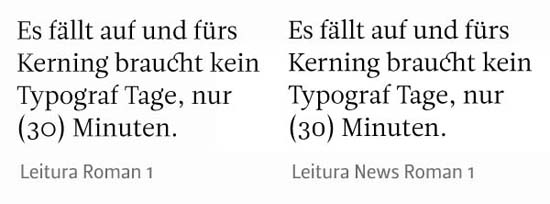
gerade habe ich das Leitura-Sonderangebot bei MyFonts gesehen. Es juckt mich ja in den Fingern: Ich bin als Naturwissenschaftler immer auf der Suche nach Schriften, die nüchtern und lesetexttauglich sind. Was ich bisher von der Leitura gesehen habe läßt mich denken, daß man sie gut auch für wissenschaftliche Aufgaben verwenden kann und die passende Serifenlose für Kapitelüber- und Bildunterschriften macht das Ganze noch attraktiver.
Meine eigentlich Frage: Hat jemand von Euch einmal mit diesem Schriftsystem gearbeitet? Wenn ich sie mir kaufe, dann möchte ich gerne sicher gehen, daß auch Details stimmen. In diesem Sinne: Weiß jemand von Euch, ob die Schriften der Leitura mit ordentlichen Kerning-Informationen daher kommen? Sicher, etwas nacharbeiten muß immer, aber manche Schriften sind weniger anfällig als andere (bei der Palatino gibt es z.B. weniger Kollisionen als bei der Garamond etc.). Und weiterhin: Ist die Leitura anständig gehintet? Ich habe mich hier einige Zeit an der Lido von Herrn Storm probiert, welche ich im Druck sehr schön finde, aber das mangelnde hinting ging mir dann nach einiger Zeit doch furchtbar auf den Geist (ja, ich weiß, einem geschenkten Gaul ...).
Weiß jemand von Euch näheres?
prinzipiell stimme ich Dir ja zu. Nun kenne ich allerdings die Verkaufspolitik von DSType nicht und habe bisher auch nicht mit Schriften von denen zu tun gehabt. Es kann ja sein, daß sie durch eine mehr oder weniger geschickt angelegte Aktion Werbung machen wollen. In diesem Fall könnte es sich durchaus um qualitativ recht hochwertige Schriften handeln. Ich bin mir durchaus bewußt, daß Qualität eben seinen Preis hat. Aber man kann eben auch einfach mal Glück haben, insbesondere bei Werbeaktionen. Habe vor Jahren mal einen originalen »Leatherman« als Werbegeschenk bekommen (natürlich mit Werbung auf dem Griff, aber wen stört sowas?). Sowas ist selten, kommt aber durchaus mal vor.
Ich hab die "Esta" von Dino dos Santos im Einsatz und kann nicht meckern (vielleicht bin ich auch nicht anspruchsvoll genug?). DSType ist halt auch ein Ein-Personen-Stück ...
ich habe auch einige von dinos fonts, kann auch nicht meckern – bis auf die namensgebung scheint alles ok zu sein. die schriften erscheinen bei mir nicht als eine familie mit schnitten im untermenü sondern alle einzeln. etwas kaotisch aber ich kann damit leben.
nach einigem Überlegen habe ich mir die Leitura tatsächlich gekauft und bin bisher insgesamt recht zufrieden. Die Namensgebung ist in der Tat etwas merkwürdig und die kursiven Schnitte erscheinen nicht als Unterpunkte, aber auch ich kann damit leben. Insgesamt denke ich, daß es sich für den Preis tatsächlich eher um ein Schnäppchen gehandelt hat.
Eines hat mich allerdings überrascht: Die mediävale Ziffer 0 der Leitura erscheint mir mißraten. Sie ist zu dünn und zu weit, reißt Löcher in den Satz:
Nun bin ich natürlich Banause. Ist das gewollt so? Gibt es einen Grund, warum die »0« so gestalltet ist, wie sie eben ist? Und den krassen Gegensatz zur 0 der Leitura News? Oder würdet Ihr zustimmen, daß das einfach nur merkwürdig aussieht? :oops:
Nicht gut – auch wenn die Type kleiner gesetzt wird, fühlt man bestimmt eine Unausgewogenheit, ein Unwohlsein, auch wenn man sich nicht für Typografie interessiert, wo einem solche Sachen "ins Gesicht springen".
Die kreisrunde mediävale Null hat durchaus ihre Berechtigung: Sie unterscheidet sich klar vom kleinen o. Umgekehrt ist ja die versale 0 wesentlich schmaler als das versale O.
Sicher muß die 0 vom o unterscheidbar sein, aber man kann die 0 der Leitura so wie sie jetzt gestaltet ist z.B. bei Geschäftsberichten mit vielen Zahlen etc. überhaupt nicht einsetzen. Es sieht einfach nur gräuslich aus. Es ist ja nicht nur die Dickte sondern sie ist eben auch im Satz viel zu dünn und reißt wo immer sie steht Löcher. Natürlich kann man argumentieren, daß sie für Geschäftsberichte die Leitura News sowieso viel besser eignet und ja offenbar auch mit einer deutlich »angepaßteren« 0 daher kommt. Ich muß allerdings gestehen, daß mir gerade die leichte Kantigkeit der Leitura recht gut gefällt. Und gerade die extreme Unterschiedlichkeit einer einzigen Glyphe zwischen den beiden Fonts finde ich schon recht überraschend. Die Leitura Sans ist da viel dichter an der Leitura News als an der Leitura. Wahrscheinlich sollte ich einfach mal Dino de Santos selber fragen ...
In Geschäftsberichten würde ich nur Tabellenziffern nehmen.
Zum größten Teil bestehen diese ja eh' aus Tabellen und in den Textteilen ist eine "herausragende" Ziffer beim schnellen Überfliegen hilfreich. Eigentlich geht es ja bei solchen Druckwerken sowieso nur um Zahlen.